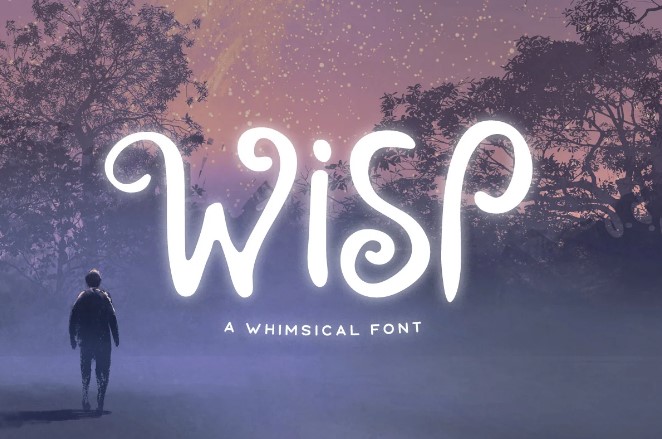
Creativemarket Wisp Font
[Creativemarket] Wisp Font
Wisp - это шрифт отображения с магическими кривыми.
Почти каждая буква имеет альтернативную версию, которую можно переключить с Caps Lock.
Шрифт включает в себя многоязычные заглавные буквы, цифры, пунктуацию и дополнительный файл шрифта с тоннами декоративных элементов.